Hướng dẫn tải font chữ tiếng Việt từ GG Fonts về máy tính nhanh chóng và đơn giản
Khi soạn thảo văn bản hay thiết kế đồ họa, font chữ đóng vai trò rất quan trọng trong việc thể hiện phong cách và cảm xúc của nội dung. Thông thường, người dùng Việt Nam hay sử dụng những kiểu chữ quen thuộc như Times New Roman, Arial, hay Calibri. Tuy nhiên, nếu bạn muốn làm mới phong cách trình bày, khiến văn bản sinh động và thẩm mỹ hơn, thì GG Fonts chính là lựa chọn lý tưởng.
GG Fonts là gì?
GG Fonts là một thư viện trực tuyến do Google phát triển, cung cấp hàng ngàn mẫu font chữ khác nhau dành cho nhiều ngôn ngữ, trong đó có tiếng Việt. Dự án này ra đời nhằm giúp các nhà thiết kế web, lập trình viên, hay người dùng phổ thông có thể dễ dàng lựa chọn và sử dụng font chữ chất lượng cao mà không cần trả phí bản quyền.
Ra mắt chính thức vào năm 2010 (và được cải tiến nhiều lần sau đó), Google Fonts nhanh chóng trở thành kho font chữ mở lớn nhất thế giới. Toàn bộ font chữ tại đây đều có thể được nhúng vào website hoặc tải về để dùng trong các phần mềm soạn thảo, thiết kế như Microsoft Word, Google Docs, Photoshop, hay Canva.
Điểm đặc biệt là tất cả font chữ trên Google Fonts đều được tối ưu cho hiển thị web, giúp văn bản rõ nét trên mọi thiết bị. Ngoài ra, thư viện này liên tục được cập nhật, thêm mới các kiểu chữ độc đáo để phù hợp với xu hướng thiết kế hiện đại.
Hiện nay, Google Fonts hỗ trợ hơn 100 ngôn ngữ, bao gồm tiếng Anh, tiếng Việt, tiếng Nhật, tiếng Hàn, tiếng Trung,… Trong đó, nhóm font tiếng Việt được thiết kế rất cẩn thận, có dấu đầy đủ và thể hiện tốt ở cả định dạng in ấn lẫn kỹ thuật số.
Cách 2: Dán thủ công vào thư mục hệ thống
Bước 1: Mở thư mục: Local Disk (C:)>Windows > Fonts.
Bước 2: Quay lại thư mục font vừa tải, nhấn chuột phải chọn Copy.
Bước 3: Quay lại thư mục Fonts và nhấn Ctrl + V để dán. Windows sẽ tự động nhận diện và cài đặt các font mới.
Sau khi hoàn tất, bạn có thể mở Word, PowerPoint hoặc Photoshop để kiểm tra. Những font chữ mới tải sẽ xuất hiện trong danh sách font và sẵn sàng để sử dụng.
Một vài lưu ý khi tải font chữ từ Google Fonts
- Kiểm tra hỗ trợ tiếng Việt: Một số font chữ quốc tế có thể chưa hỗ trợ đầy đủ dấu tiếng Việt. Trước khi tải, bạn nên gõ thử đoạn văn có dấu (Ví dụ: “Tôi yêu tiếng Việt”) để xem font hiển thị có chính xác không.
- Không cần cài đặt từng file: Nếu bạn tải Download family, file sẽ bao gồm toàn bộ các kiểu chữ của font. Việc cài một lần sẽ tự động thêm tất cả.
- Tối ưu cho thiết kế web: Nếu bạn làm website, Google Fonts có sẵn đoạn mã HTML/CSS để chèn trực tiếp. Chỉ cần sao chép dòng code và dán vào phần <head> của trang web là có thể hiển thị đúng font.
- Tương thích hệ điều hành: Google Fonts hoạt động tốt trên Windows, macOS và Linux.
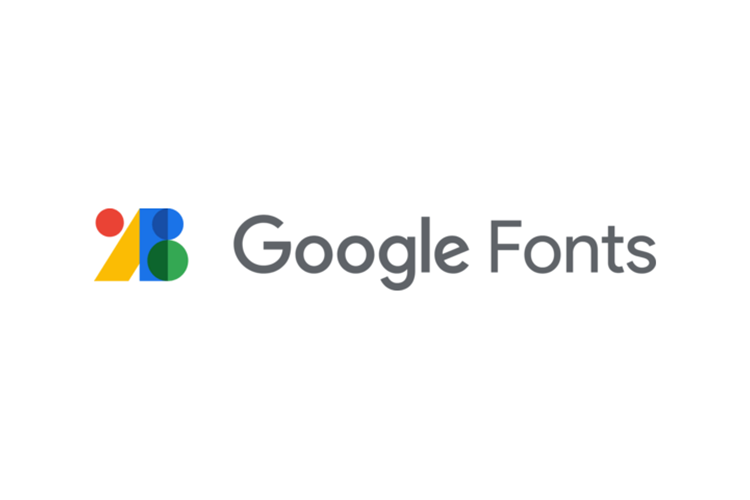
Gợi ý một số font tiếng Việt đẹp trên Google Fonts
Nếu bạn chưa biết chọn font nào, dưới đây là vài gợi ý nổi bật:
- Roboto: Kiểu chữ hiện đại, dễ đọc, phổ biến trong thiết kế web.
- Open Sans: Font chữ cân đối, thân thiện, hiển thị tốt trên cả màn hình lớn và nhỏ.
- Montserrat: Phù hợp cho tiêu đề, poster, mang phong cách sáng tạo.
- Lora: Font chữ serif nhẹ nhàng, thích hợp cho nội dung dài hoặc bài viết học thuật.
- Quicksand: Font tròn mềm mại, hiện đại, phù hợp cho thiết kế trẻ trung.
Tạm kết
GG Fonts là công cụ tuyệt vời dành cho bất kỳ ai muốn làm mới văn bản hoặc website của mình bằng những kiểu chữ độc đáo và đẹp mắt. Với hàng ngàn lựa chọn miễn phí, hỗ trợ đầy đủ tiếng Việt, cùng khả năng cài đặt dễ dàng, bạn hoàn toàn có thể tải font chữ tiếng Việt từ GG Fonts chỉ trong vài phút!